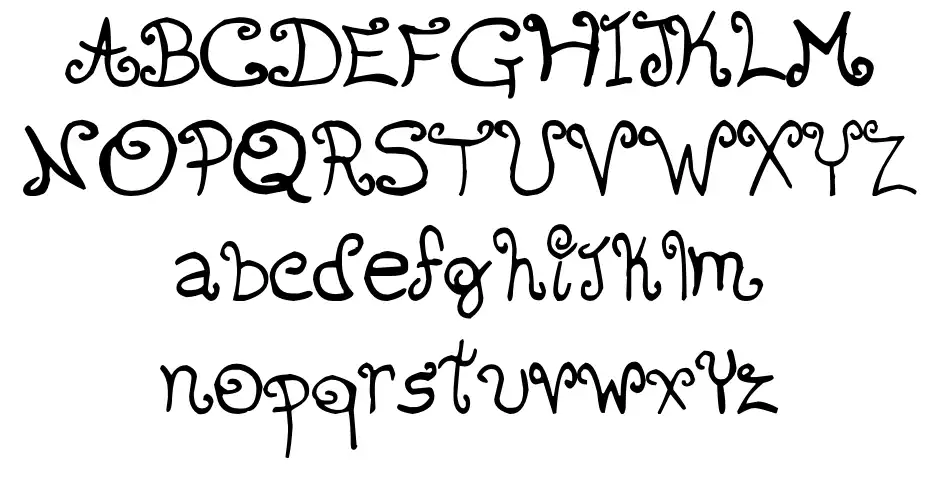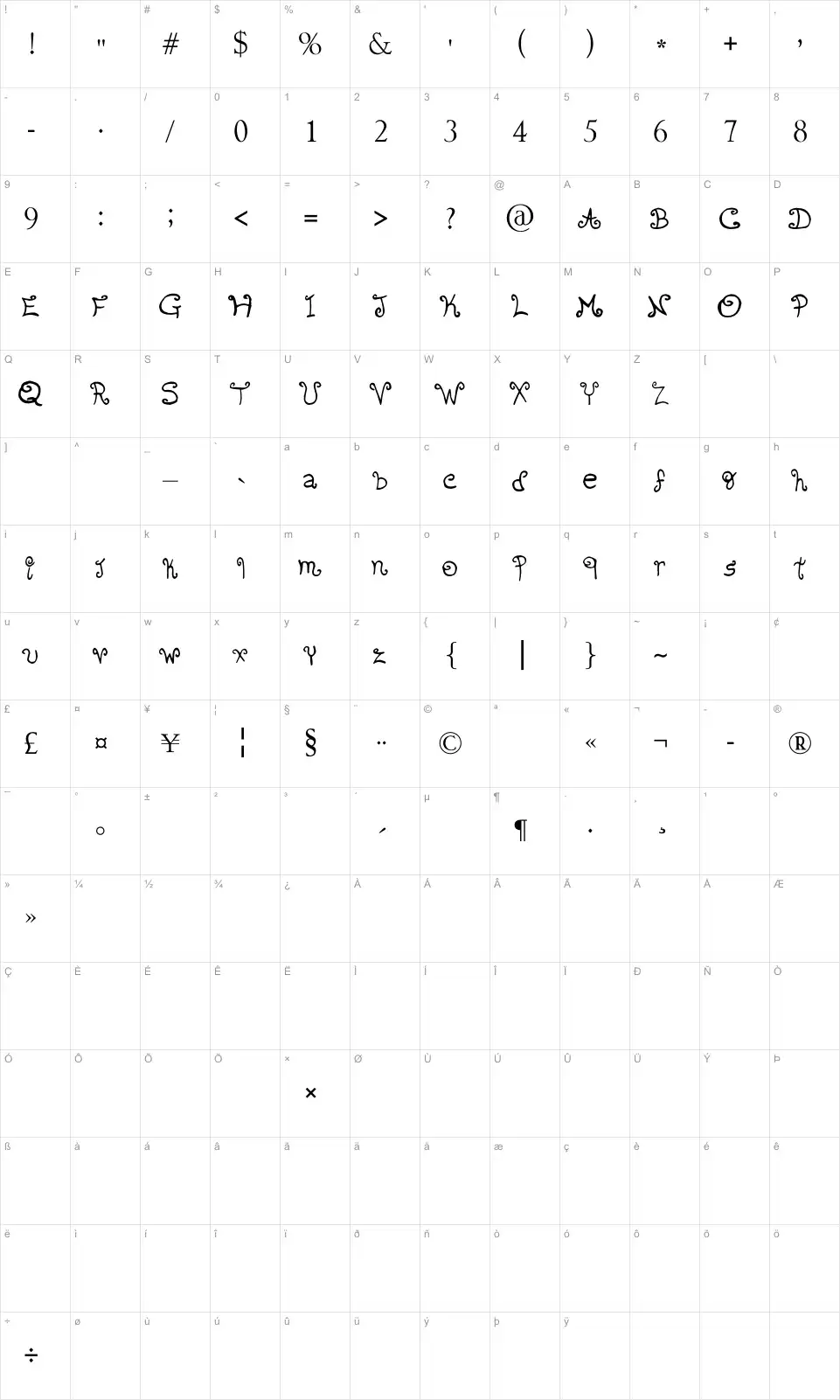
A fonte ‘Romantic Font 2’, criada por Martina Cullen, é perfeita para adicionar um toque de sofisticação e elegância a seus projetos digitais. Esta fonte, categorizada como Fancy e com um estilo Curly, oferece uma maneira única de destacar seu texto. Se você está procurando por essa fonte ou quer experimentá-la antes de usá-la, você pode facilmente fazer download ou gerar um preview personalizado de texto online. Adicionada em 13 de julho de 2022, a fonte já teve mais de 3600 downloads. Com um tamanho de 16 KB, ela é compacta e ideal para usar em projetos digitais de pequeno a médio porte. Essa fonte está disponível gratuitamente para uso pessoal, tornando-a uma ótima opção para designers e criativos.
Categoria: Fancy › Curly
Designer: Martina Cullen